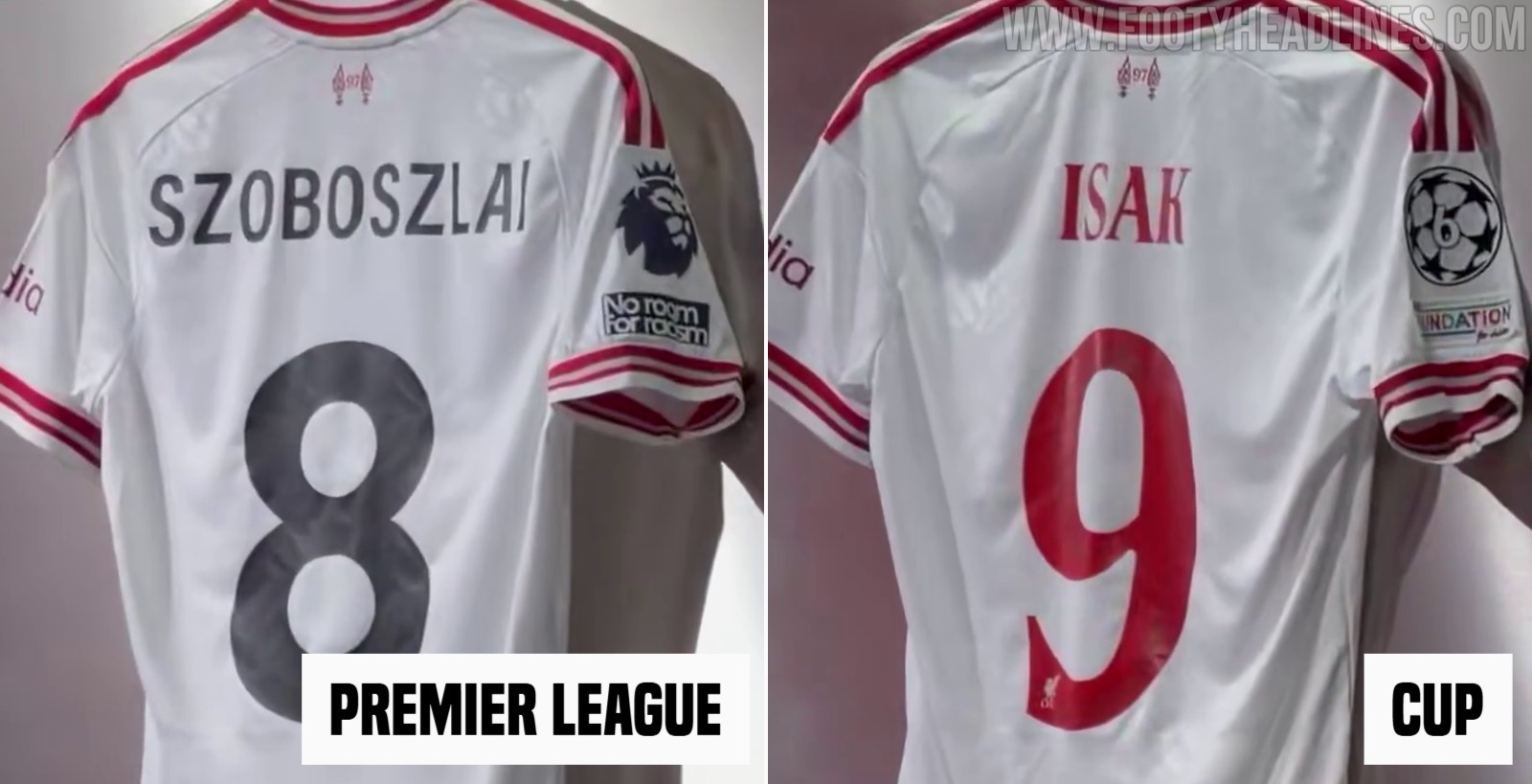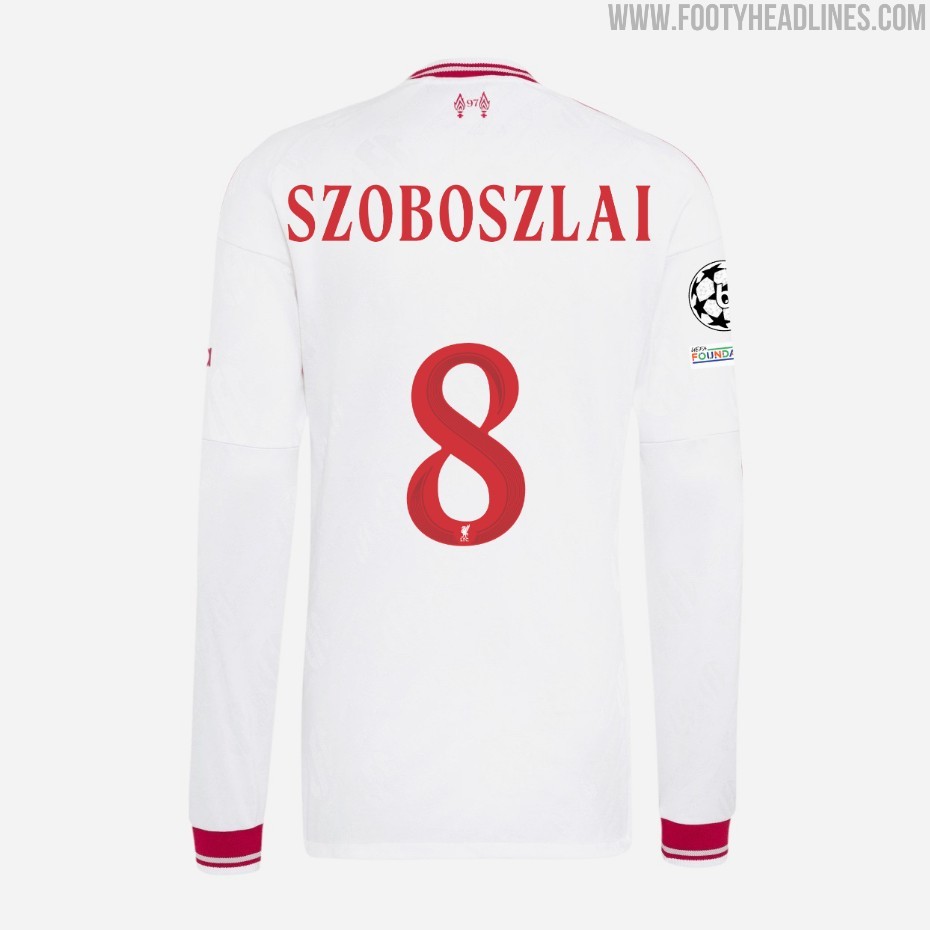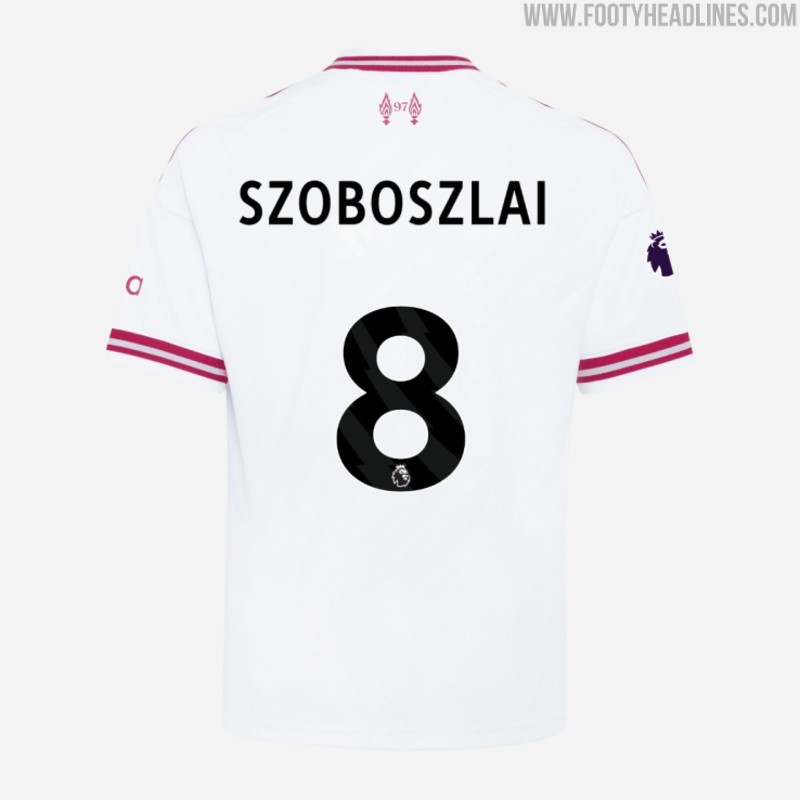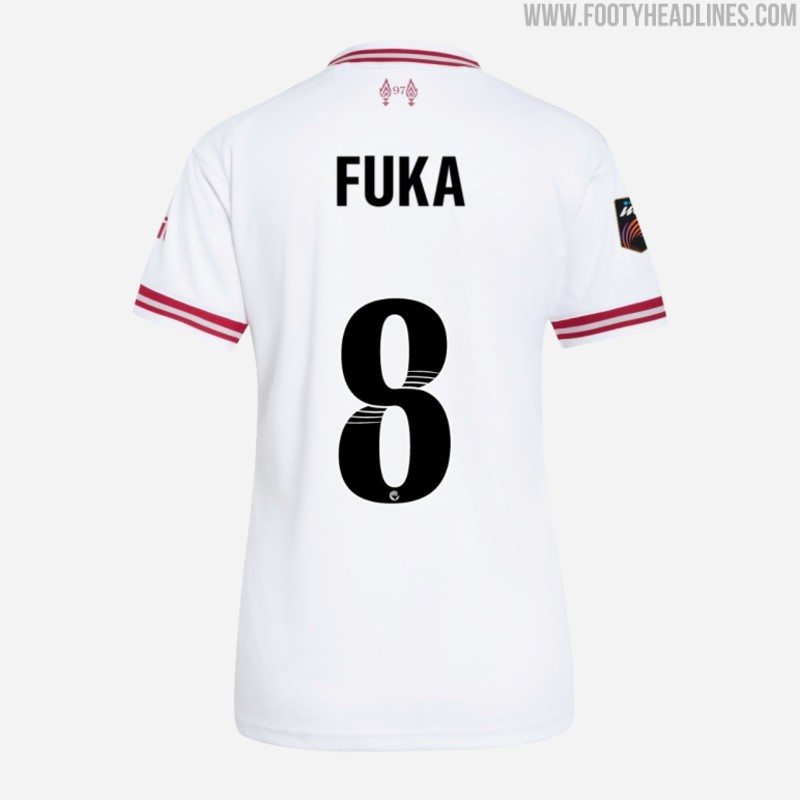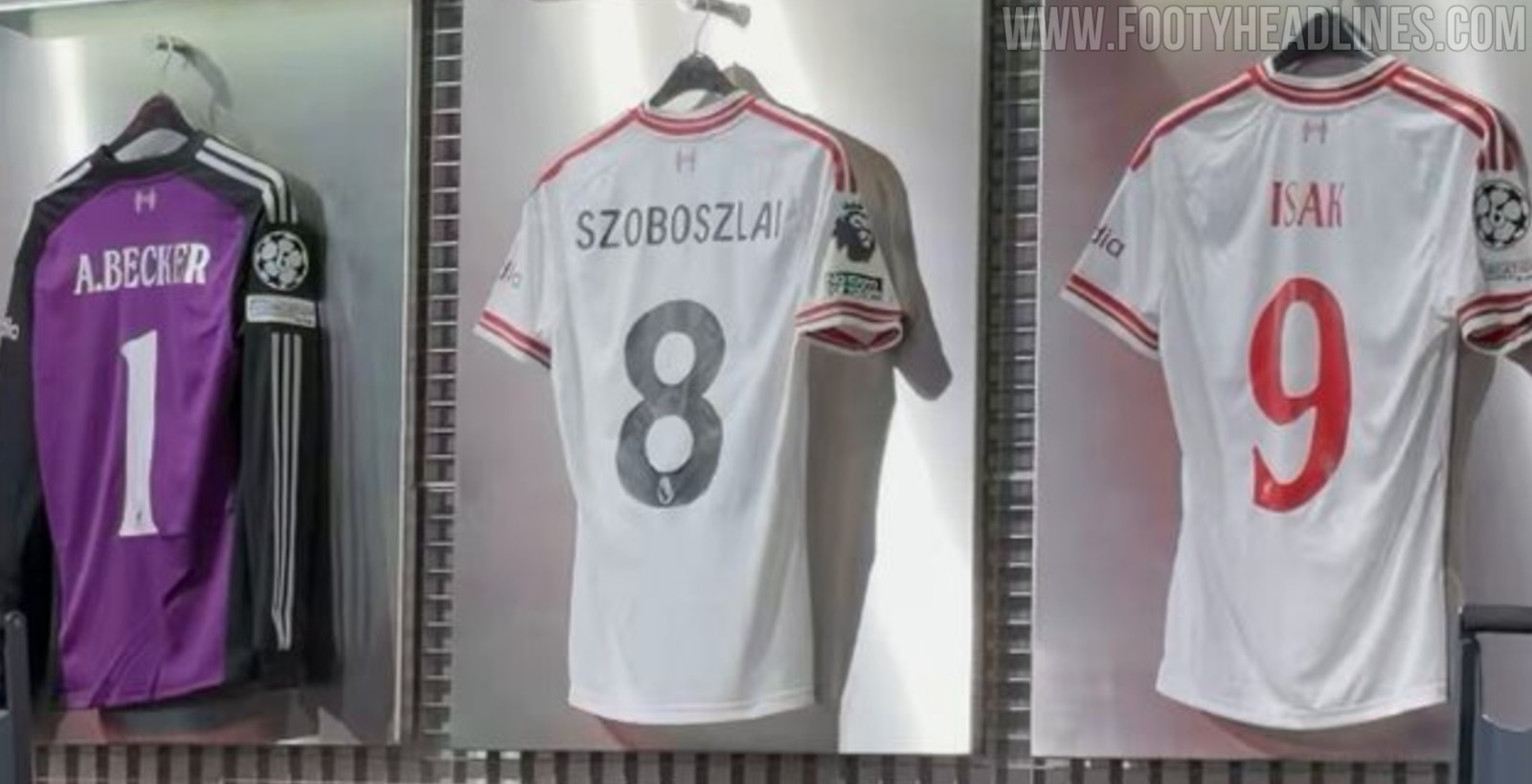
La seconda maglia del Liverpool 26-27 presenta il font nero della Premier League
• Lancio e Design Retrò: La seconda maglia 26-27 del Liverpool è stata ufficialmente presentata da Adidas, caratterizzata da uno stile retrò con il classico logo Trefoil e lo storico stemma Liver Bird degli anni '80, con una base bianco sporco e dettagli rossi.
• Carattere della Premier League in Nero: Per le partite di Premier League, la seconda maglia del Liverpool presenterà scritte e numeri neri sul retro, una scelta sorprendente probabilmente dovuta a una discordanza di tonalità tra il rosso della maglia e quello del carattere semplificato della EPL.
• Carattere delle Coppe in Rosso: Nelle partite di coppa, il Liverpool userà un nuovo font da coppa in rosso abbinato, il quale, in modo anomalo, include il logo Liverbird standard con la scritta LFC nonostante la maglia sfoggi una versione classica del Liver Bird.
Il Liverpool ha presentato ufficialmente la sua seconda maglia 26-27 in stile retrò, realizzata da Adidas e caratterizzata dal classico logo Trefoil insieme allo storico stemma Liver Bird degli anni ’80. La scelta dei colori per il carattere tipografico ha sorpreso molti – grazie a ++Jay Pearson++ di Tops of the Kop per la segnalazione.
Il design della maglia da trasferta del Liverpool 26-27 presenta una base bianco sporco impreziosita da audaci dettagli rossi sul colletto, sulle strisce sulle spalle e sui polsini delle maniche. Ci sono solo questi due colori, più il grigio per i dettagli. Tuttavia, la maglia avrà un quarto colore in campo durante le partite di campionato.
Per le partite di Premier League, la seconda maglia del Liverpool 2026-2027 presenta scritte e numeri neri sul retro, e non quelli rossi disponibili come una delle 5 opzioni predefinite. Probabilmente questo dipende dal fatto che il carattere rosso semplificato della EPL ha una tonalità di rosso diversa da quella della maglia. Anche la versione WSL presenta un carattere nero.
Nelle partite di coppa, il Liverpool userà il suo nuovo font da coppa, in rosso abbinato. Stranamente, il font presenta il logo Liverbird standard con la scritta LFC, anche se la maglia ne ha uno classico.